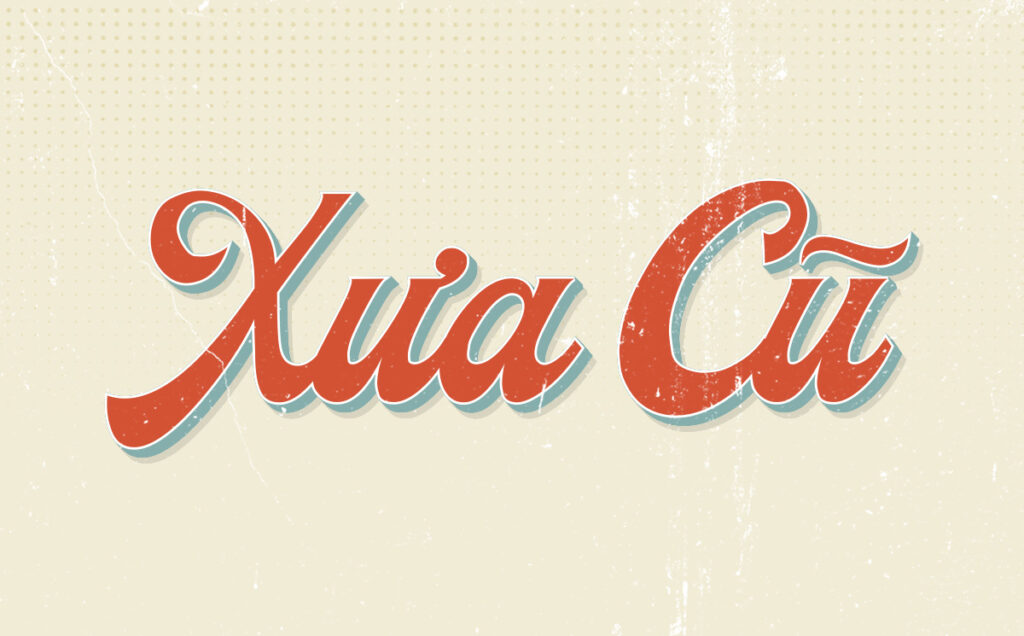
Phông chữ mang phong cách Sài Gòn xưa gợi nhắc về những biển hiệu vẽ tay đặc trưng của những thập niên trước, mang trong mình linh hồn của sự hoài niệm và nét văn hóa đường phố độc đáo. Việc sử dụng font chữ Sài Gòn xưa Việt hóa free giúp các kiến trúc sư, nhà thiết kế thổi hồn vào các dự án homestay, quán cafe hay bộ nhận diện thương hiệu một cách đầy nghệ thuật.
Đặc điểm thẩm mỹ của bộ font chữ Sài Gòn xưa Việt hóa
Khác với những kiểu chữ in ấn hiện đại có phần cứng nhắc, font Sài Gòn xưa Việt hóa sở hữu sự mềm mại tự nhiên, gợi lên hình ảnh của những tiệm tạp hóa, rạp hát hay các biển chỉ dẫn giao thông cũ. Bản Việt hóa đã xử lý tinh tế hệ thống dấu thanh, giúp các dấu hỏi, ngã, nặng được đặt ở vị trí cân đối, không làm phá vỡ nhịp điệu hoài cổ của bộ chữ gốc.
Sự ổn định về mặt thị giác của dòng font này còn nằm ở khả năng khơi gợi cảm hứng về sự bền vững và gần gũi. Trong kiến trúc hiện đại, việc sử dụng các phông chữ mang âm hưởng quá khứ tạo ra sự cân bằng thị giác thú vị khi phối hợp với các vật liệu mới như thép, panel hay kính. Đây là lựa chọn phù hợp cho những ai muốn khẳng định cá tính riêng và tư duy thẩm mỹ nhân văn trong từng sản phẩm sáng tạo.
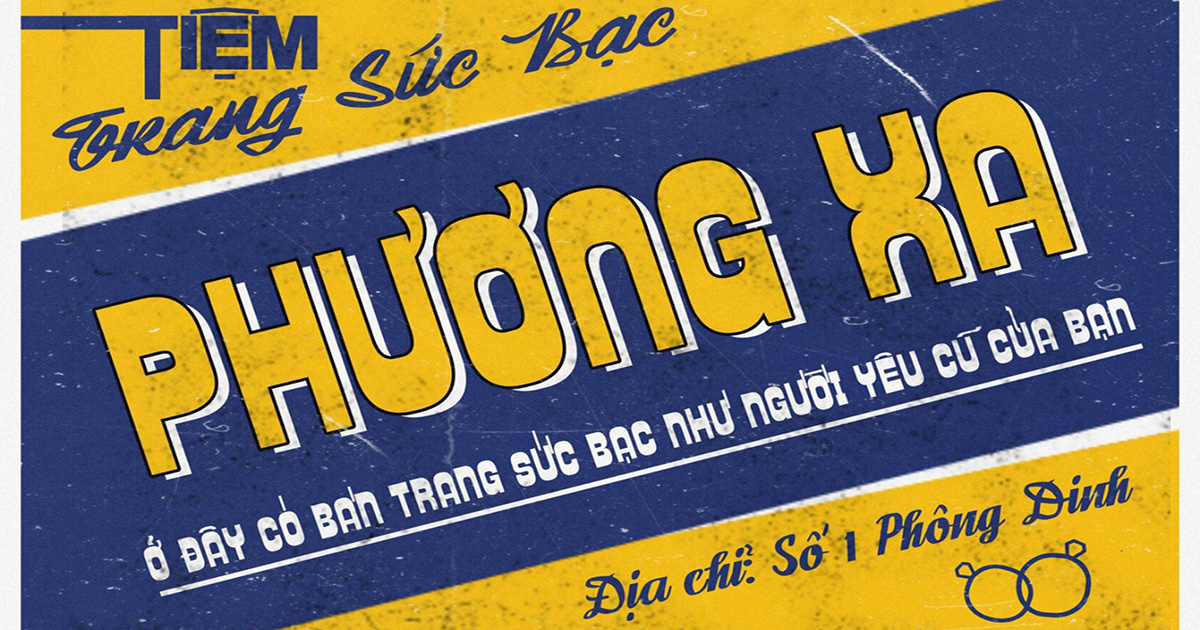
| Phân loại phong cách | Retro / Vintage / Sign Painting |
| Nhóm phông tiêu biểu | Hòn Ngọc Viễn Đông, Gia Định, Giá Rẻ Việt hóa |
| Mục đích phù hợp | Bảng hiệu hoài cổ, Poster, Decor nội thất |
Tư vấn trình bày: Phông chữ phong cách Sài Gòn xưa thường có độ đậm lớn. Để bản thiết kế đạt được hiệu quả thẩm mỹ ổn định, bạn nên phối hợp font chữ Sài Gòn xưa free cho các tiêu đề chính và sử dụng một phông chữ không chân tối giản cho phần nội dung thuyết minh chi tiết, giúp tổng thể bố cục trông chuyên nghiệp hơn.
03 Ứng dụng font Sài Gòn xưa Việt hóa vào thực tế kiến trúc
Nhờ vẻ ngoài giàu tính gợi hình và chiều sâu văn hóa, bộ phông chữ này mang lại giá trị cao trong khâu trang trí và quảng bá các công trình hiện đại:
- Bảng nhận diện cho Homestay & Khu nghỉ dưỡng Vintage: Những nét chữ hoài cổ rất ăn ý khi xuất hiện trên chất liệu gỗ hoặc alu phủ màu trầm tại các khu nhà lắp ghép nghỉ dưỡng. Font chữ này giúp không gian toát lên vẻ ấm cúng và thu hút du khách yêu thích vẻ đẹp xưa cũ.
- Trang trí không gian nội thất Retro: Bạn có thể dùng font này để làm tranh quotes trang trí hoặc cắt chữ nổi đèn neon tại phòng khách, khu vực sảnh chờ văn phòng container nhằm tạo điểm nhấn đầy lôi cuốn và khơi gợi cảm hứng sáng tạo.
- Thiết kế bộ quà tặng doanh nghiệp: Sử dụng font chữ Sài Gòn xưa Việt hóa trên các nhãn dán sản phẩm hoặc thiệp tri ân giúp thương hiệu tạo được ấn tượng về sự tỉ mỉ, trân trọng các giá trị truyền thống đối với khách hàng.
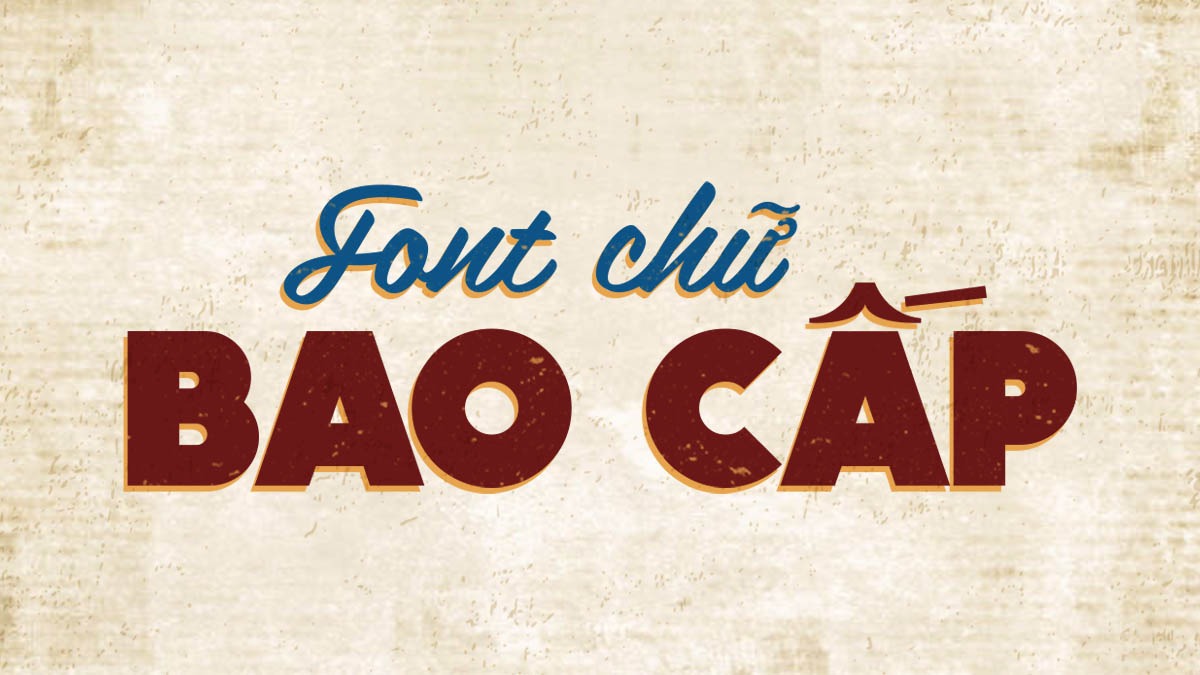
03 Lưu ý để bố cục font chữ Sài Gòn xưa chuyên nghiệp và hài hòa
Để khai thác hiệu quả vẻ đẹp của dòng font đặc thù này mà không làm rối mắt người xem, người thiết kế nên lưu tâm một số lưu ý kỹ thuật sau:
- Lựa chọn màu sắc mang tính thời đại: Phong cách hoài cổ phát huy hiệu quả thị giác cao khi phối cùng các tông màu như vàng nghệ, cam cháy, xanh rêu hoặc đỏ bordeaux. Tránh các màu quá chói lọi làm mất đi vẻ sang trọng, trầm mặc của bộ chữ.
- Kiểm soát khoảng cách dòng: Do cấu trúc chữ thường có các nét vươn rộng, bạn nên để khoảng cách dòng thoáng một chút để các dấu thanh tiếng Việt không bị chồng lấn, giữ được sự minh bạch cho văn bản khi nhìn từ xa.
- Hạn chế dùng cho văn bản dài: Chỉ nên sử dụng tải font chữ Sài Gòn xưa cho các tiêu đề lớn, slogan hoặc các cụm từ nhấn mạnh. Việc lạm dụng cho các đoạn thuyết minh kỹ thuật dài sẽ gây mỏi mắt và làm giảm tính thẩm mỹ của hồ sơ dự án.